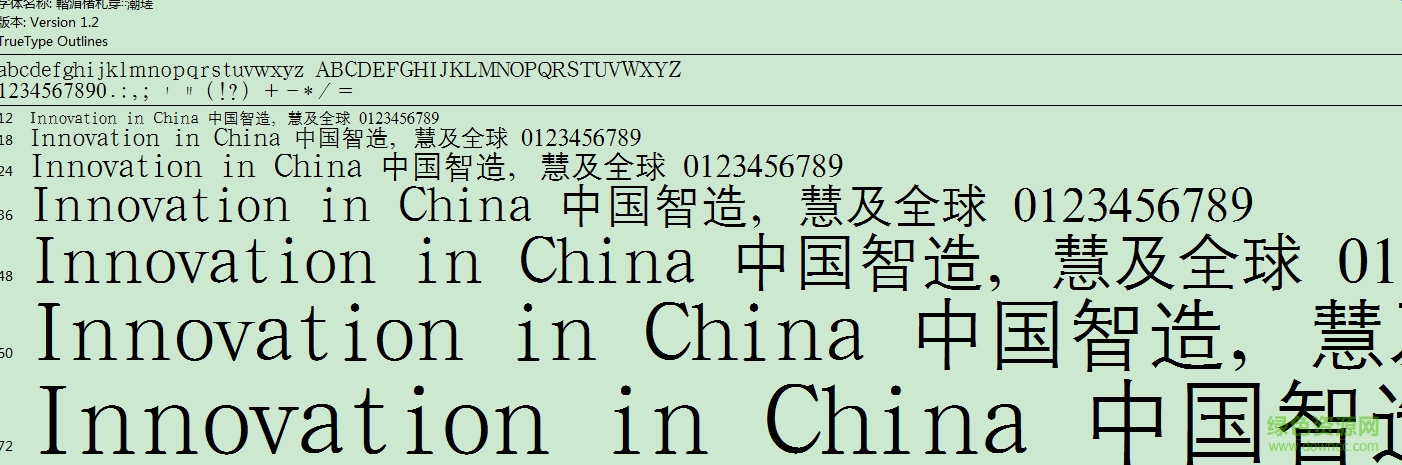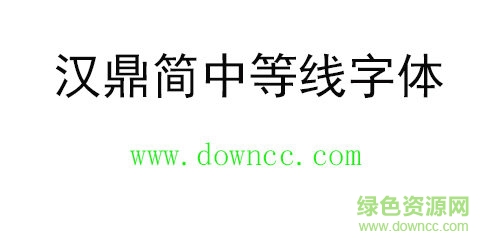
漢鼎簡中等線字體
漢鼎簡中等線字體是一款漢鼎字體,用途廣泛,可以用于廣告設(shè)計(jì)、海報(bào)設(shè)計(jì)等等方面,它能讓你在設(shè)計(jì)時(shí)界面變得更加美觀,還能和別的字體進(jìn)行混搭,非常的實(shí)用,有需要的朋友快來綠色資源網(wǎng)免費(fèi)下載哦。